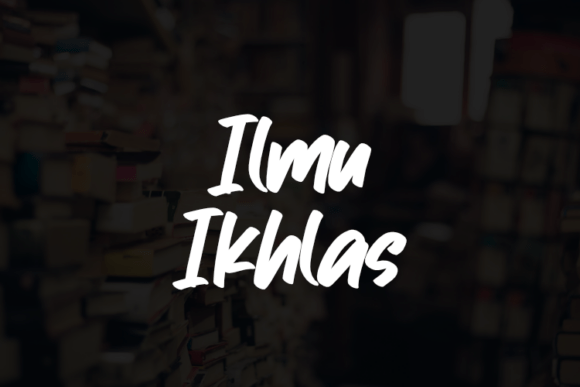
Ilmu Ikhlas
適切なデザイン要素を見つけるのは難しい場合がありますが、Ilmu Ikhlasは作品を即座に引き立てる優れたコレクションを提供します。
精密に作られたIlmu Ikhlasは、クリーンなベクター、滑らかなタイポグラフィ、そして安心のための商用ライセンスを提供します。
POD(オンデマンド印刷)製品、結婚式の招待状、またはソーシャルメディアのグラフィックを作成している場合でも、Ilmu Ikhlasは理想的です。